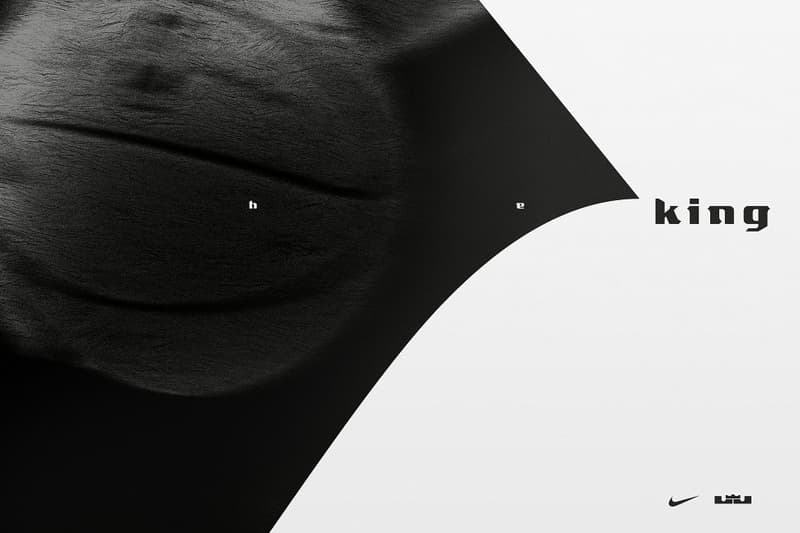
LeBron James 帝皇之字体,敲定!
曾应 Nike Basketball 之邀替 Kevin Durant and Kobe Bryant 产品设计专属字体的 Creative agency Sawdust,最新任务是替大帝 LeBron James 创造霸气字体。根扎伦敦的二人组 Jonathan Quainton 与 Rob Gonzalez 最近接受 Designboom 访问,解释新字体怎样反映大帝个性;勇猛、强大、精神之余,还要有帝皇气质。计划的隐性挑战是新字体将会经常与 Kobe 和 KD 专属字体在同一个空间短兵相接,两人组经过细心摸索,设计出眼前的帝皇字体。大家可有被霸气所震慑?